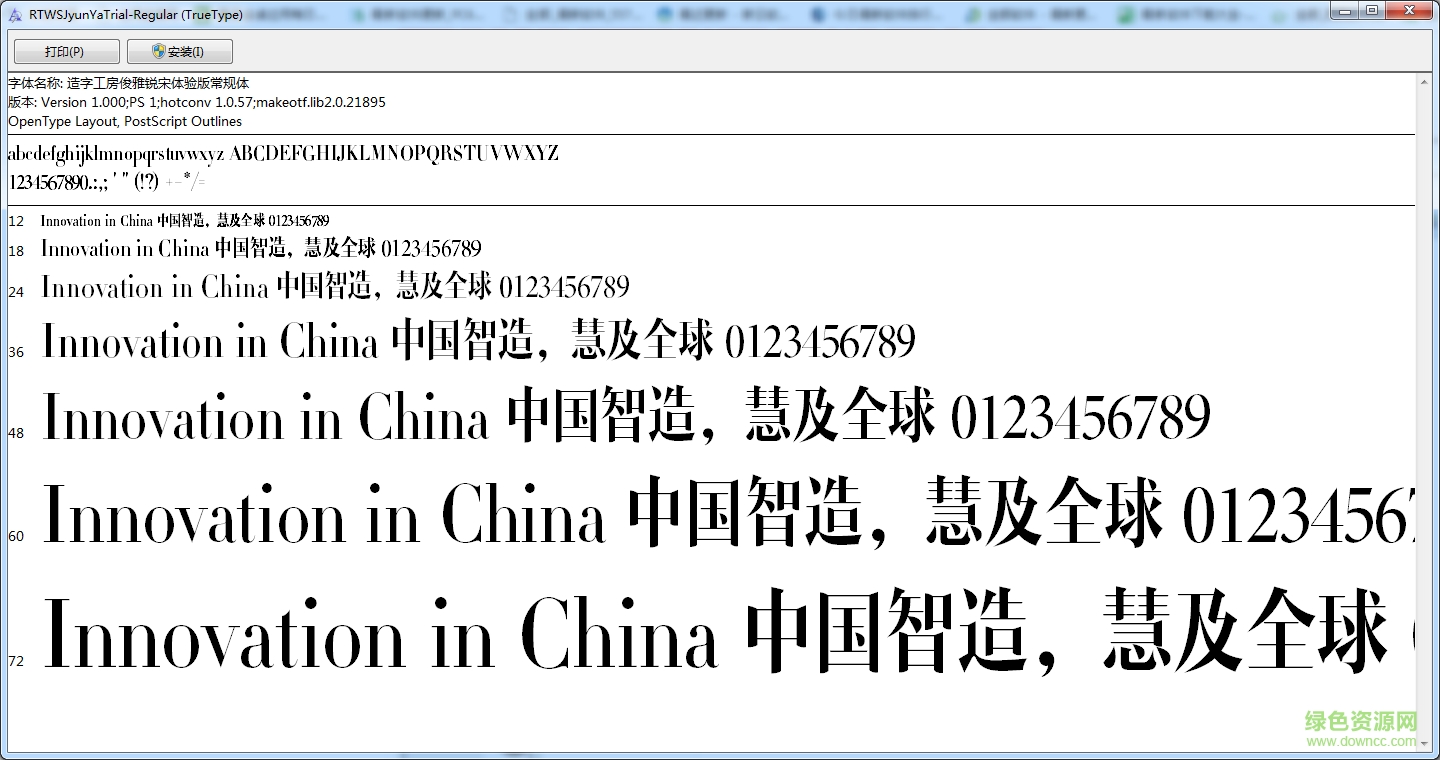
造字工房俊雅銳宋體驗(yàn)版常規(guī)體
造字工房俊雅銳宋字體是一款簡(jiǎn)潔美觀的中文簡(jiǎn)體字體,此款字體大小均勻,字庫(kù)完整,整體效果相當(dāng)不錯(cuò),安裝方法簡(jiǎn)單快捷,應(yīng)用范圍非常廣泛,喜歡的朋友歡迎來綠色資源網(wǎng)下載!